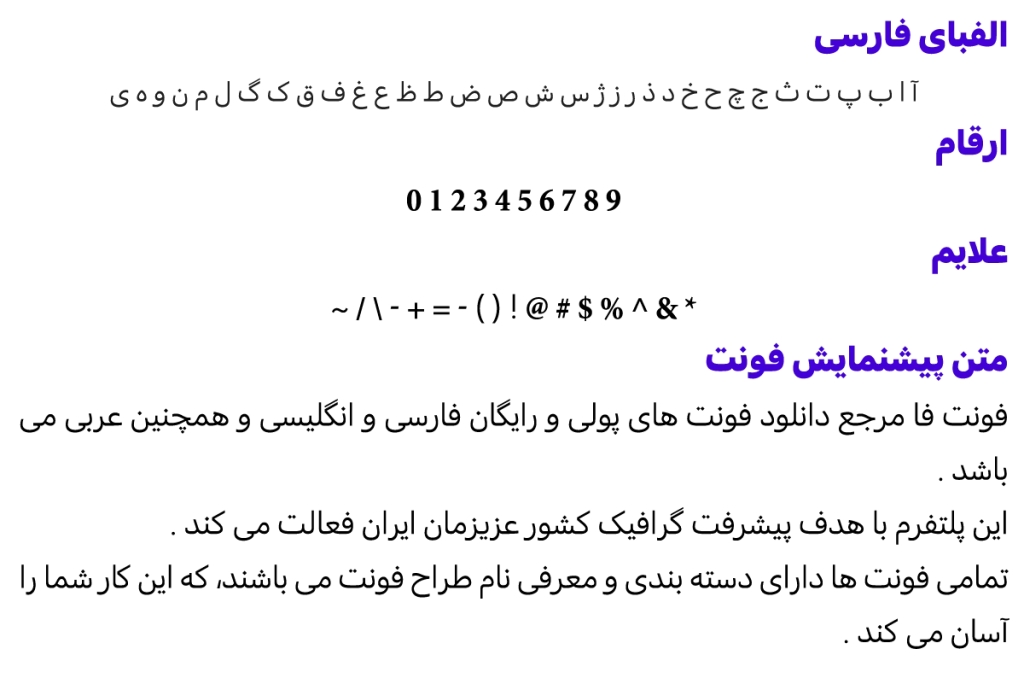
فونت آیفون اپل - SF Arabic
توضیحات و معرفی فونت آیفون
فونت فارسی – عربی آیفون ( SF Arabic ) از مجموعه فونت های آزاد می باشد، همچنان نوع فونت مناسب طراحی وب، عنوان و متن می باشد.
فونت شگفت انگیز و زیبای فوق در سال 2024 توسط شرکت اپل آمریکا برای گوشی های این شرکت طراحی و ساخته شده است.
این فونت دارای حروف گ چ پ ژ نیز می باشد که نسخه ایرانی شده این تایپ فیس می باشد.
همچنان فونت آیفون در 10 وزن پر رنگ و سنگین و حروف سنگین و سبک و متوسط و معمولی و نیمه پر رنگ و نازک و فوق سبک و وریبل است.
در لیست زیر می توانید وزن های این فونت شگفت انگیز و زیبا را ببینید.
1. SF Arabic Bold
2. SF Arabic Black
3. SF Arabic Heavy
4. SF Arabic Light
5. SF Arabic Medium
6. SF Arabic Regular
7. SF Arabic DemiBold
8. SF Arabic Thin
9. SF Arabic UltraLight
10. SF Arabic Variable
در این تصویر شعر زیبای ایران نوشته شده با این فونت محبوب را می توانید مشاهده کنید.